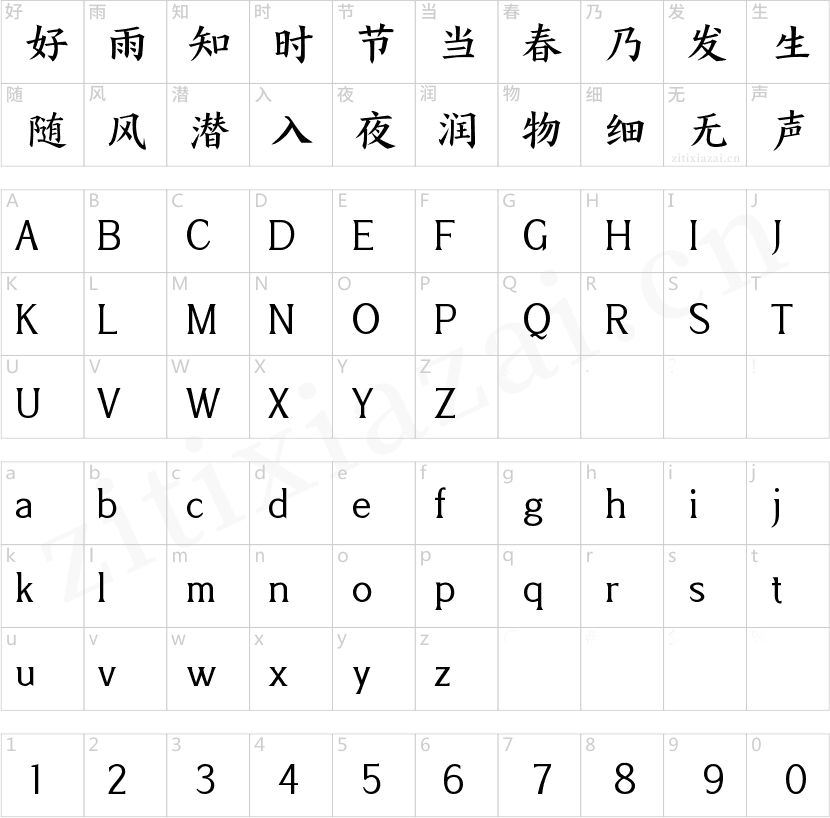
Aa扁雅楷
Aa扁雅楷字体
Aa扁雅楷是一款非常具有艺术性的字体,它的设计灵感来源于对古典艺术的研究,同时又融入了现代字体设计的元素。字形优美,笔画粗细变化自然,给人以大气、典雅的感觉。Aa扁雅楷是一款既传统又现代的字体,它的设计充满艺术感,美观大方,实用性也非常强。无论是对于设计师还是对于普通读者来说,都是一种非常不错的字体选择。Aa扁雅楷适合用于具有艺术感的场合,比如海报、宣传单张、书籍封面等。由于其字形流畅且具有动态感,也适合用于大量的文本排版,如报纸、杂志等。